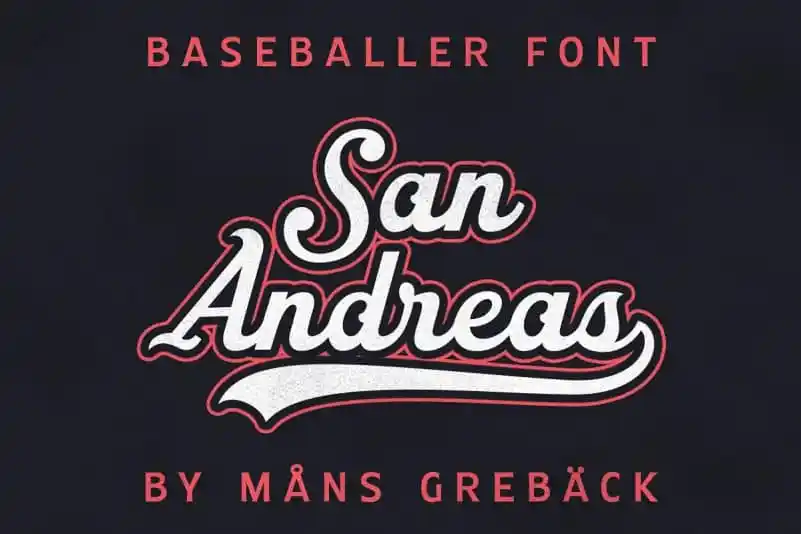
San Andreas Script Font
A San Andreas Script Font é uma deliciosa escolha para quem busca um tipo script que não apenas destaca no ambiente do seu projeto, mas também oferece suporte a múltiplas línguas. Criada pelo designer Mans Greback, ela inclui letras maiúsculas e minúsculas, números e símbolos adicionais, além de caracteres com acentuação para facilitar o uso internacional. Esta fonte atinge uma mistura de estilos vintage retro e robustez vintage, incorporando a essência dos materiais antigos brincando na mão com linhas firmes e suaves pinceladas. Ideal para aplicativos em que o estilo retrô seja desejado, como logotipos ou design editorial, ela se destaca por sua facilidade de legibilidade, mesmo quando usada em tamanhos pequenos. Seja para um projeto pessoal ou corporativo, a San Andreas Script Font é uma escolha inteligente para aqueles que valorizam tanto a beleza quanto o poder de comunicação visual. Não perca essa oportunidade de adicionar um toque único e versátil à sua identidade visual com a San Andreas Script Font.